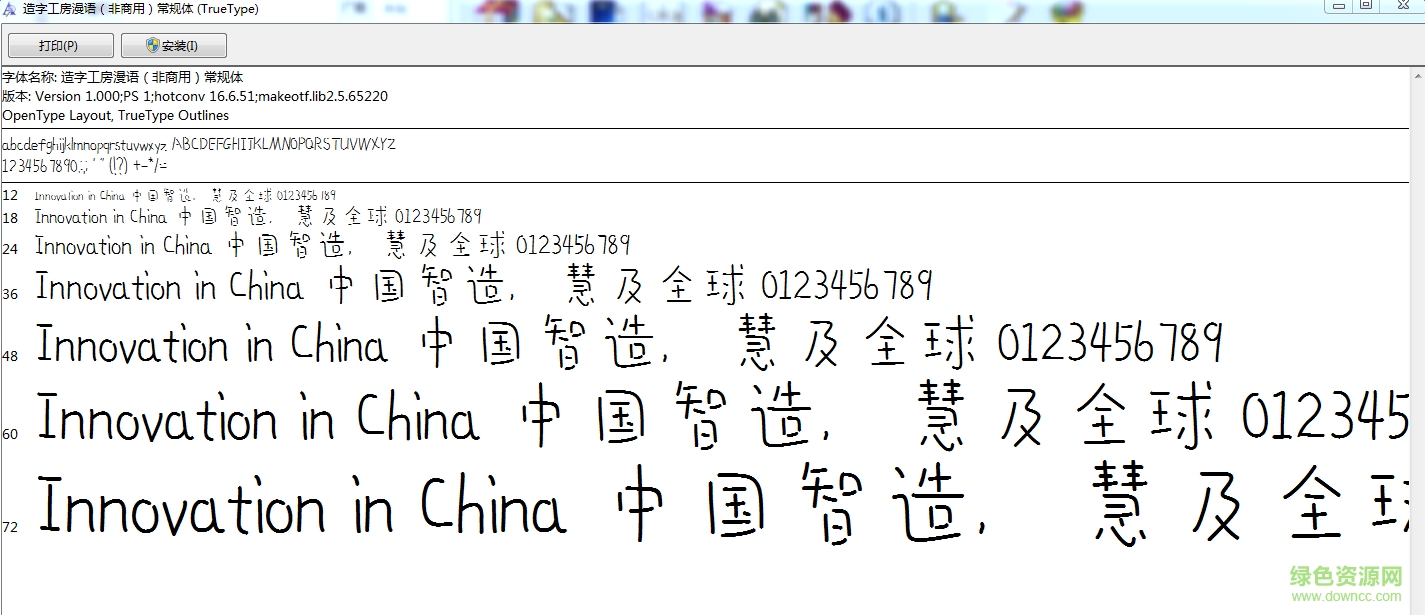
造字工房漫语体是一款造字工房类生动可爱风格字体软件,漫语体整体给人天真浪漫的感觉,适用于儿童书籍、娱乐杂志等方面,还有更多好看字体尽情期待,欢迎到绿色资源网下载体验!
造字工房漫语体结构自然洒脱,字形活泼、可爱,造型生动有趣,具有灵活的适用性。此款字体适用于儿童读物、报刊杂志标题、广告设计等视觉环境,有着极强的应用空间。